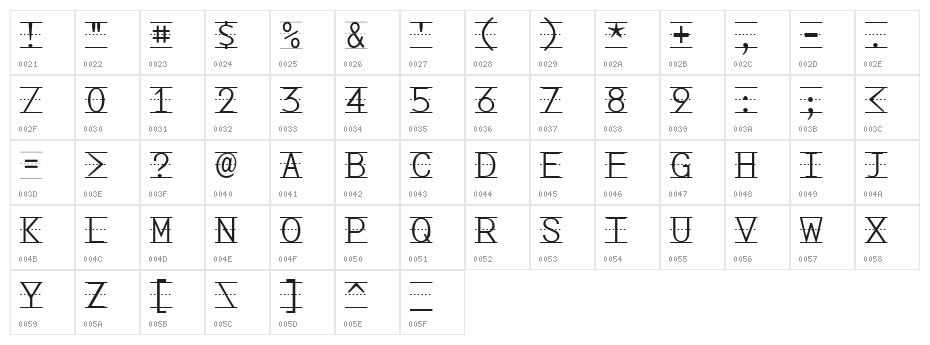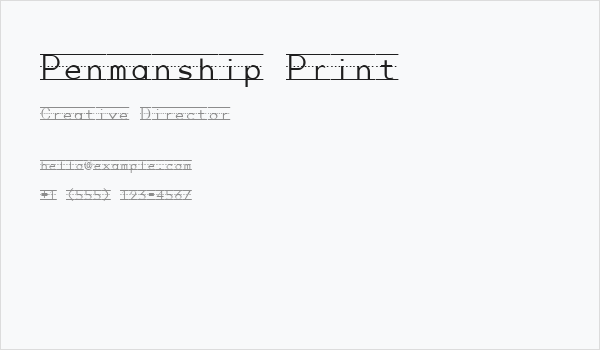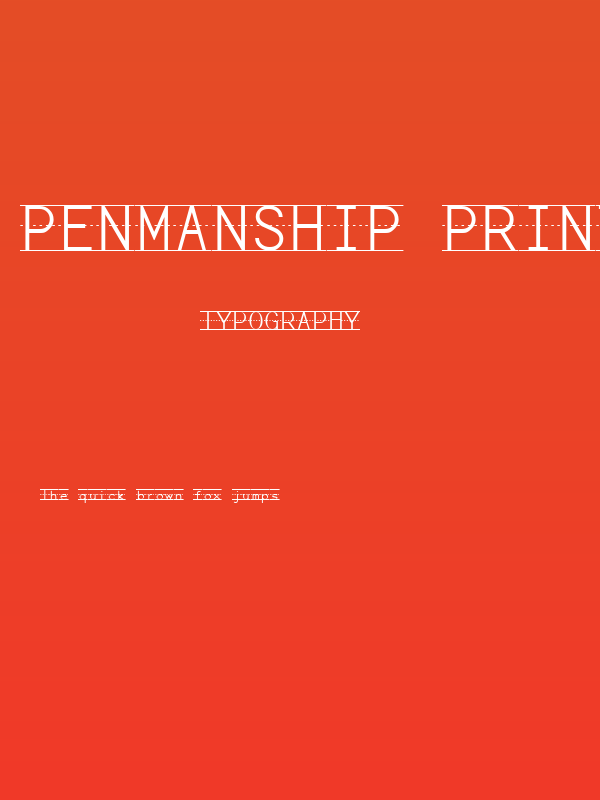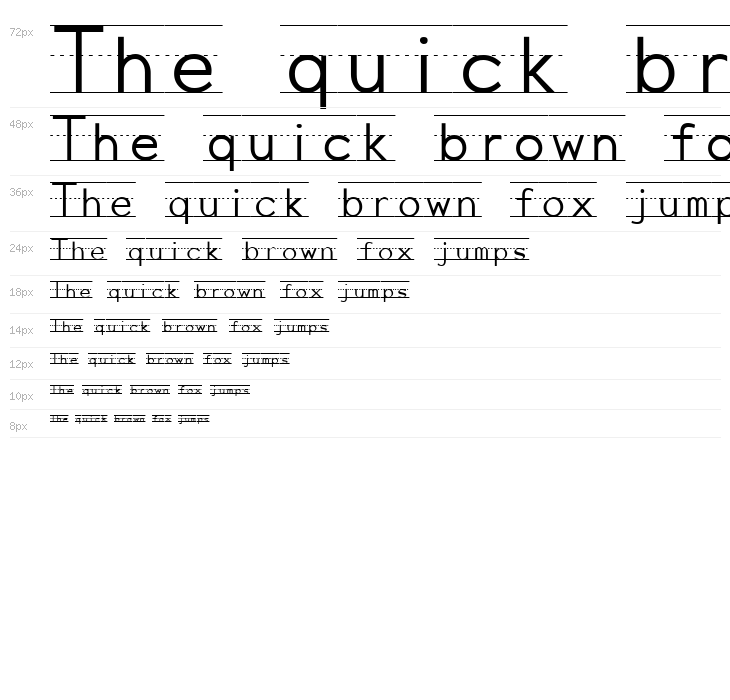
Penmanship Print Font
| Estilo general | Classic |
| Caso de uso | Educational materials, instructional guides, children's books. |
| Proyectos propuestos | Ideal for educational materials, children's books, instructional guides, and any project requiring a clear and approachable typeface. |